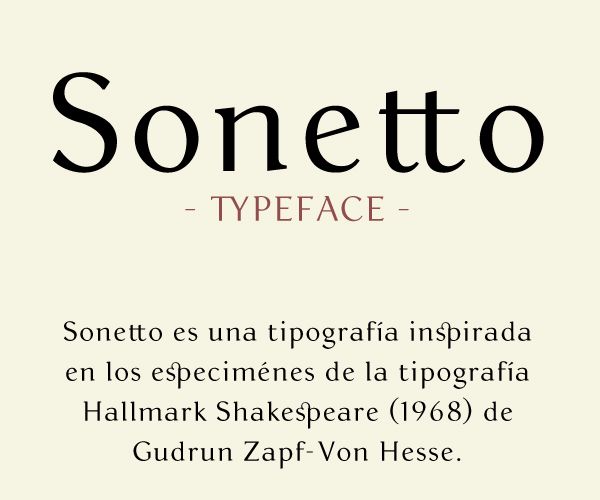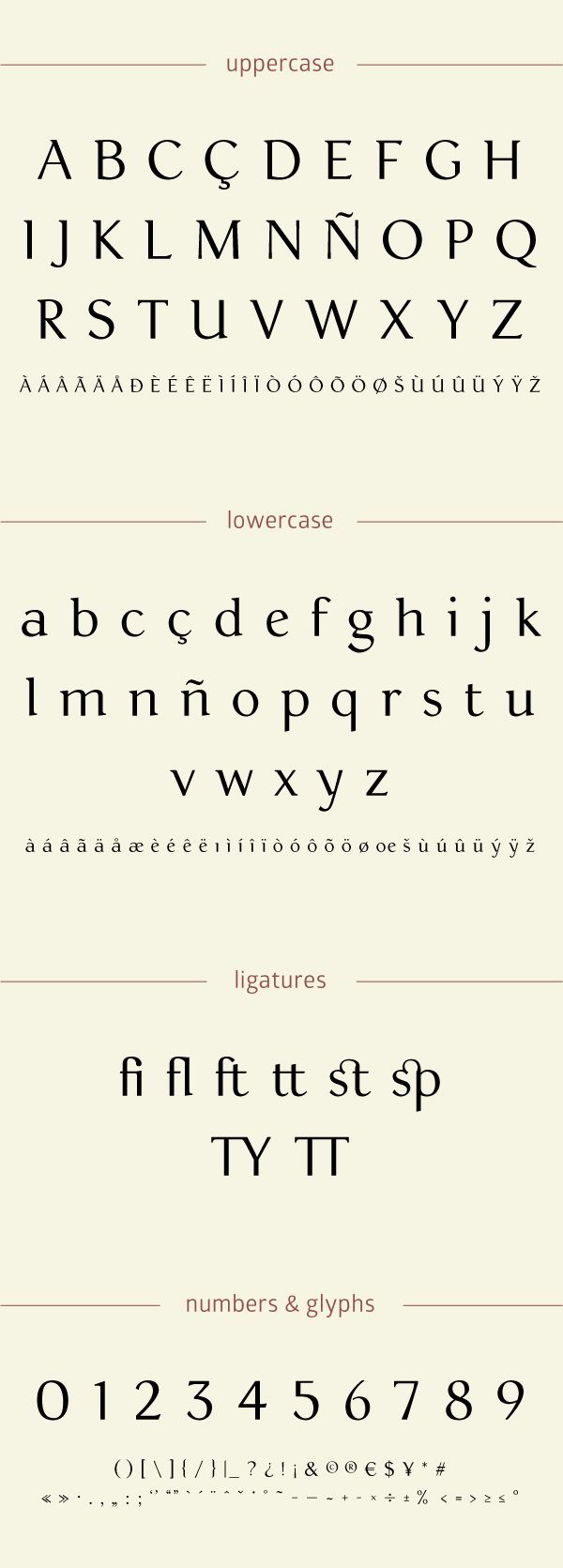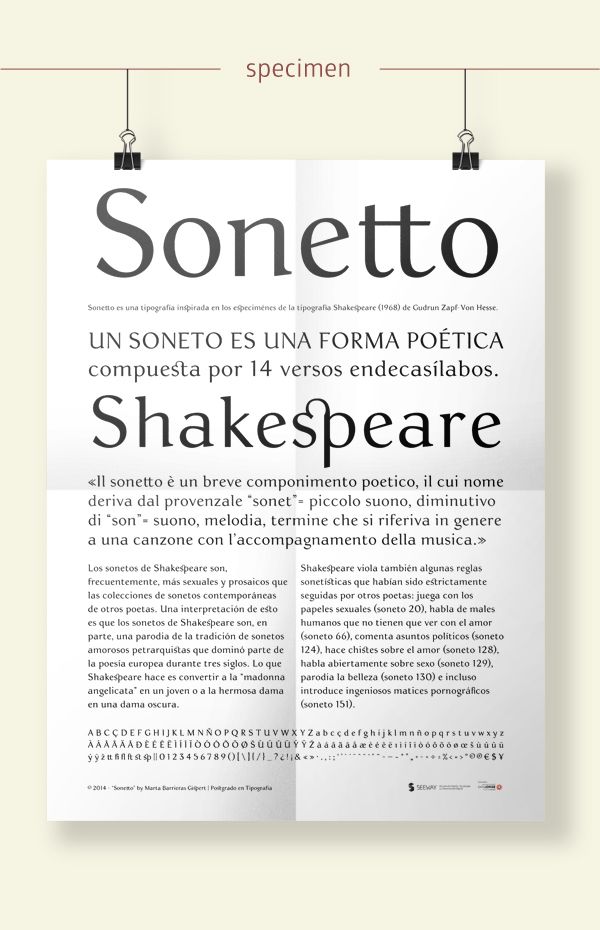
Julio 2014 ( proyecto final Postgrado)
Sonetto es una tipografía inspirada en los especímenes de la tipografía Hallmark Shakespeare (1968) de Gudrun Zapf-Von Hesse.